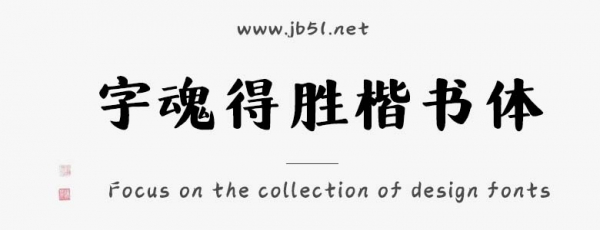
字魂得勝楷書體是由字魂字庫推出的楷體字體,該包含9503個中文、字母、 符號和數(shù)字,具有中國風(fēng)的風(fēng)格,可以滿足您設(shè)計上的各種需求,適合應(yīng)用于藝術(shù)設(shè)計、平面宣傳設(shè)計、網(wǎng)頁設(shè)計,書法字帖等領(lǐng)域。
字魂得勝楷書字體是一款商用的楷體,毛筆書法,書法字字體,該字體包含9503個中文、字母、 符號和數(shù)字,具有中國風(fēng)的風(fēng)格,可以滿足您設(shè)計上的各種需求,該字體主要用于標(biāo)題等場景, 您不但可以在字魂網(wǎng)下載字魂得勝楷書字體,同時還有眾多毛筆書法字體、創(chuàng)意字體等可供選擇!